La première cartouche.
En retraçant l’évolution des lettres, nous avons reconstitué, un peu par surprise, celle de leurs significations. La disposition qui en ressort sur le manège équestre est identique à celle que nous connaissons, ce qui répond à la question originelle : qu’avons-nous sous les yeux ?
Les manèges et les stades équestres antiques dont le grand Circus Maximus de Rome ont la plus célèbre des formes culturelles connues, le cartouche.
C’est un rectangle aux bords arrondis dans lequel on grave ou peint des hiéroglyphes contenant les noms de ce qui est important, divin ou pharaonique.
Si les Egyptiens ont bien créé un cartouche équestre, ce que nous allons étudier maintenant, nous pourrons en déduire qu’il était d’une grande importance en tant qu’outil de formation. De plus, informés de leur goût immodéré pour la métaphore religieuse, nous devrions y retrouver des messages fondamentaux.
En appliquant au manège contemporain les signes Egyptien ancestraux correspondant aux lettres, nous obtenons un disposition instructive. Au point que l’on va regarder d’un peu plus près ce que les chevaux étaient pour les Pharaons et comment et pourquoi ils auraient crée cet outil de formation.
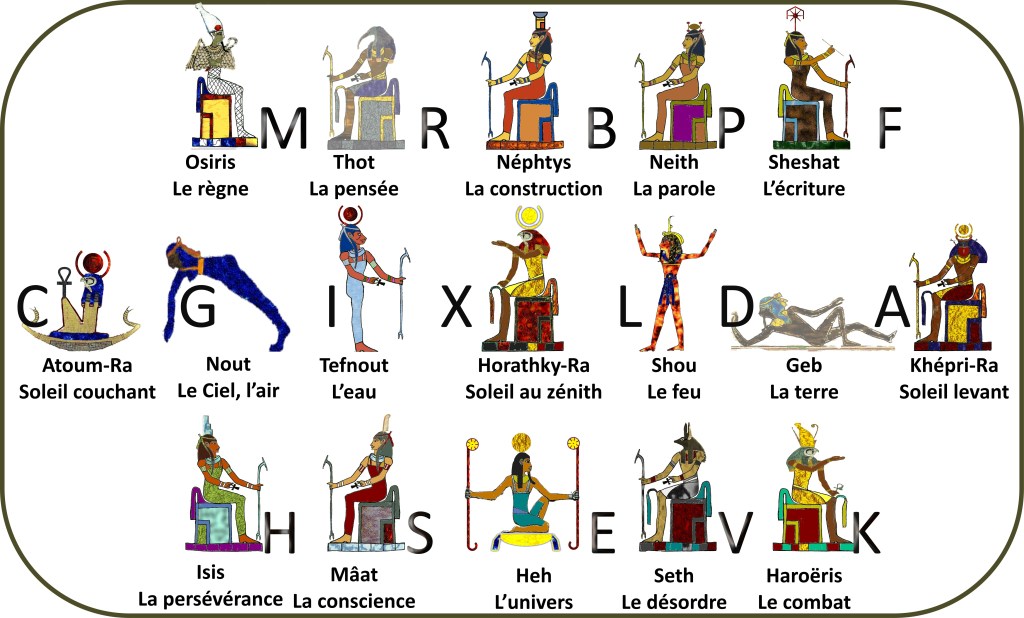
Gloire au Cheval Tardif.
C’est décevant pour celles et ceux qui en connaissent les immenses qualités, mais La triste réalité nous force à constater que le cheval n’est pas un dieu pour les Égyptiens.
Il n’existe pas dans leur Panthéon de divinité hybride à tête de cheval, ni d’âne, ni même de poney. Les chevaux sauvages ne peuplaient pas la Haute-Egypte à l’orée du récit mythique. Ils sont arrivés, domestiqués, bien plus tard, du nord, avec les « envahisseurs étrangers ».
L’histoire de la guerre équestre nous apprend que les Sumériens ont longtemps conservé plusieurs coups d’avance sur leurs adversaires. Chez eux, les pratiques de l’élevage, du dressage et de l’exploitation armée des équins remonteraient à – 4 700 ans.
Pendant ce temps-là en Egypte, les têtes à adorer s’inspiraient d’animaux familiers plus ou moins approchables, à commencer par les crocodiles, hippopotames, serpents, scarabées et scorpions.
Des bestioles intimidantes et dangereuses qui vivent le long du grand fleuve et dans les déserts.
Leur mythologie intégrera les grands félins, les faucons, les ibis et les babouins, sans oublier les girafes et les chacals. Des bêtes en cours de domestication et d’exploitation rempliront aussi leurs rôles : les ovins, les bovins et les caprins, voilà de bons modèles.
Pour être complets, n’oublions pas de mentionner les animaux qui tentèrent de domestiquer les humains : les puces et les rats qui échouèrent en partie, tandis que les chats réussirent de façon éclatante et pérenne.
Que l’on se rassure, le cheval devint en quelques foulées le chouchou des Égyptiens, à commencer par être celui des plus importants d’entre eux : les Pharaons.
Même Pas en Zèbre.
Non divinisé en Haute-Egypte, l’équin se rattrape en figurant copieusement sur certaines illustrations tombales parmi les plus connues. Depuis environ – 1540, il se pavane sur les fresques consacrées à la conquête de la Basse-Égypte lors du règne guerrier de Ahmôsis 1er.
Sa fonction n’est pas le travail de bât, c’est bien la guerre et il figure comme le plus utile et respecté des instruments vivant des batailles. Pharaon aime ses chevaux : il les commande sur son char et les tient à ses côtés pendant les célébrations et les actions religieuses.
L’illustration d’un Roi Divin, le réunificateur, l’un des plus importants de tous en tant que grand amateur d’équins, forme la charnière de l’histoire cavalière d’Égypte et révèle la principale explication de l’existence du manège antique et de son marquage si particulier.
Avant Ahmôsis 1er, les chevaux ne sont pas mentionnés mais pendant son règne et après lui, ils deviennent omniprésents dans tous les domaines importants de la vie de l’aristocratie d’Égyptienne.
Pourtant, il existe un espace de vie on ne peut plus sérieux dans lequel l’équidé n’intervient pas : la mort. Où sont leurs momies ?
Connaissant la tendance ancestrale des Égyptiens les plus riches à se faire ensevelir avec ce qui leur sera utile dans l’au-delà, on s’attend à trouver des équidés, momifiés, décharnés et vidés de leurs viscères, dans les grandes tombes. Il n’en est rien. (Jusqu’à présent car les fouilles continuent.)
Nous pourrions penser que les momies de chevaux ont disparu, ce qui ne serait pas surprenant, le pillage des riches sépultures royales, parfois à l’instigation de Pharaons désargentés, fut une façon de se transmettre des valeurs.
Toutefois, le cheval est resté la monture des guerriers et n’a pas été attelé en Egypte Pharaonique en tant qu’animal de bât. Pour cela il y avait des ânes et des bœufs.
Pour les dromadaires, il faudra attendre vers – 400 avant que leur usage se généralise. En matière de transports il faut garder en mémoire que l’Egypte est avant tout un pays fluvial et maritime.